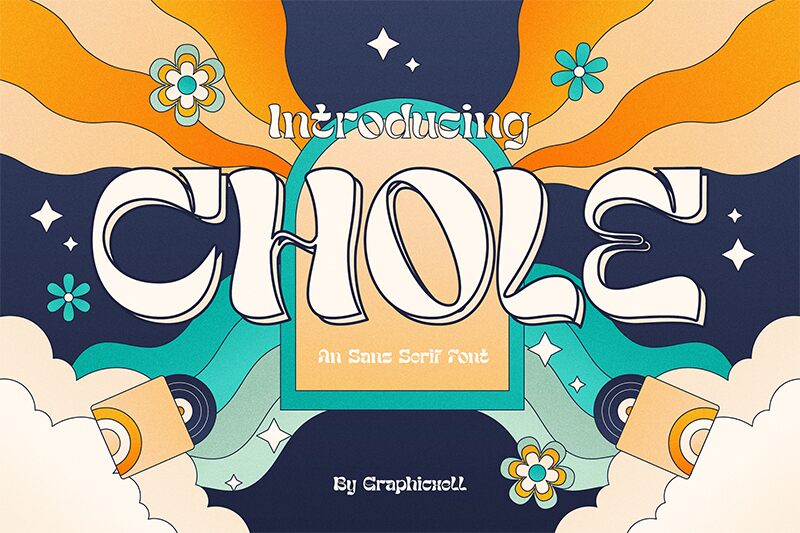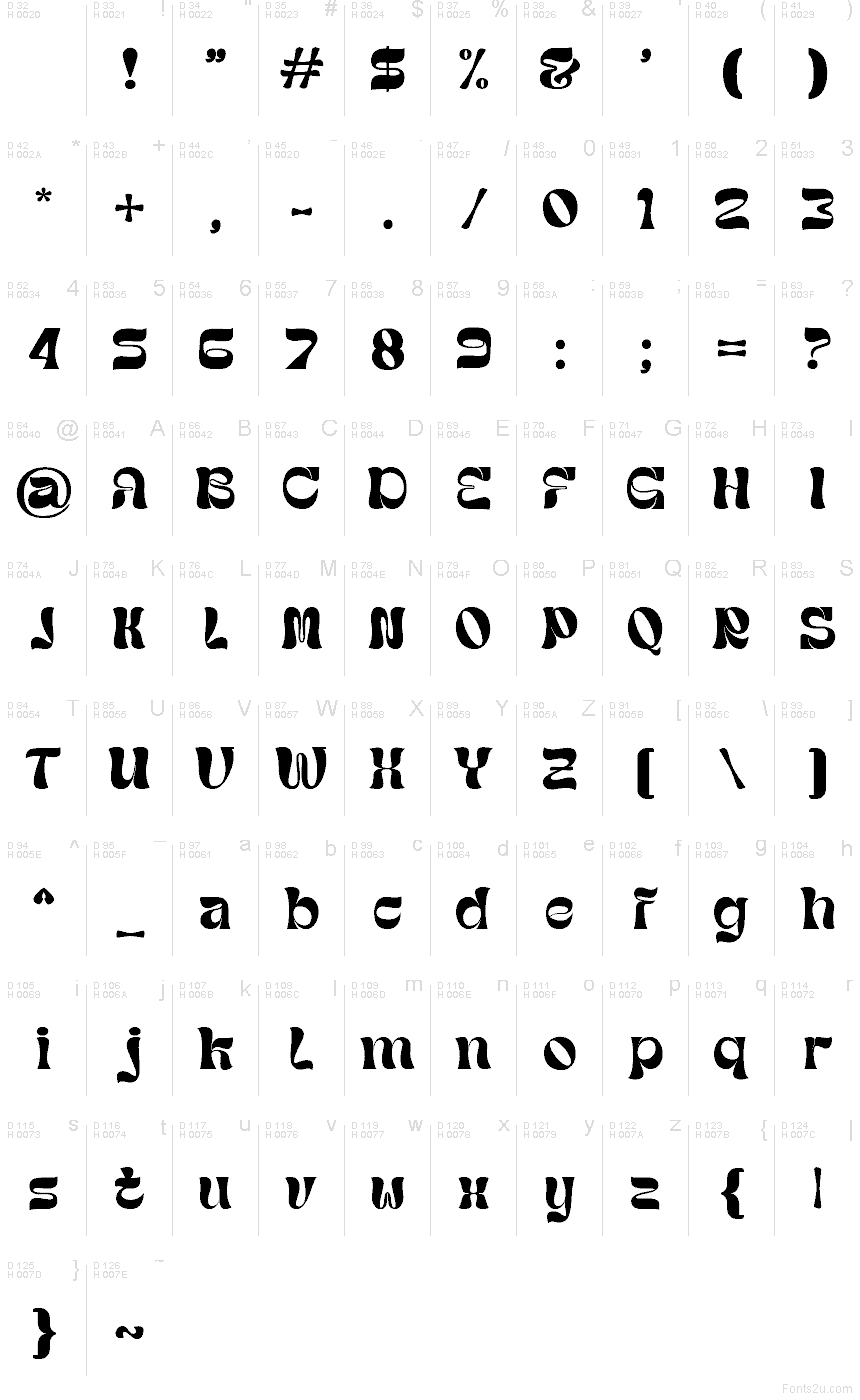
Chole di Graphicxell è un font display groovy gratuito caratterizzato da lettere arrotondate e ondeggianti, con finali morbidi e incurvati che gli conferiscono un ritmo fluido e artigianale. Le forme appaiono ricche e decorative senza risultare confuse, mantenendo uno stile fluido e armonioso in ogni parola.
Chole è perfetto per titoli di poster, copertine di album, flyer di festival, loghi e packaging che richiedono un tocco retro distintivo. Questo font gratuito è ideale anche per la segnaletica di boutique e per le grafiche sui social media, poiché le sue forme sinuose donano un carattere decorativo unico ai testi brevi che devono catturare l'attenzione.